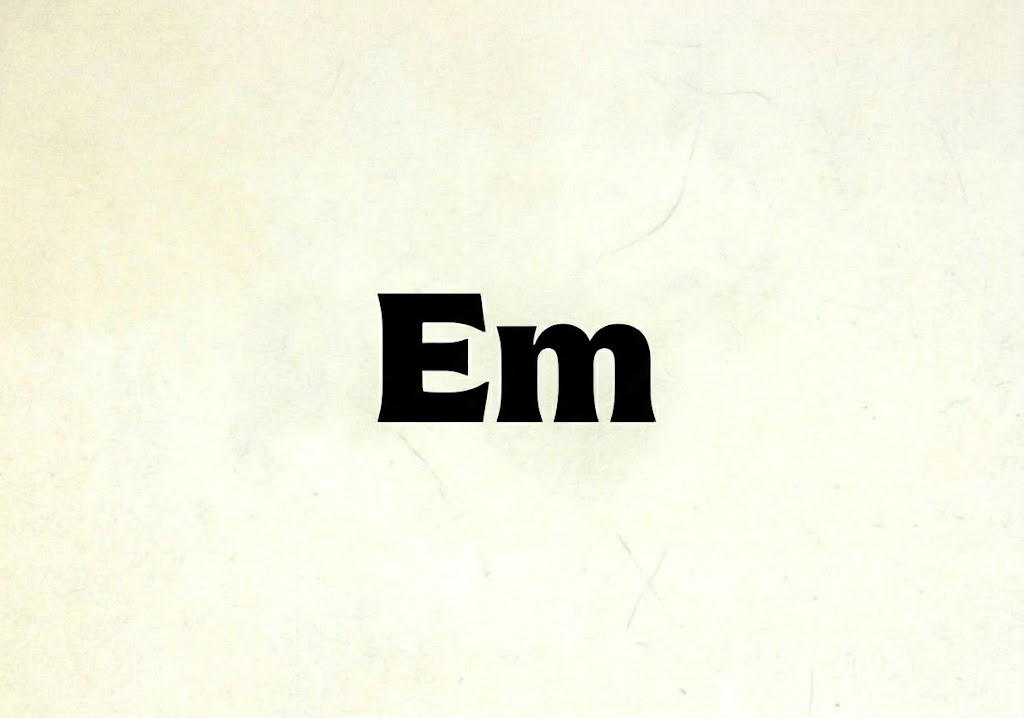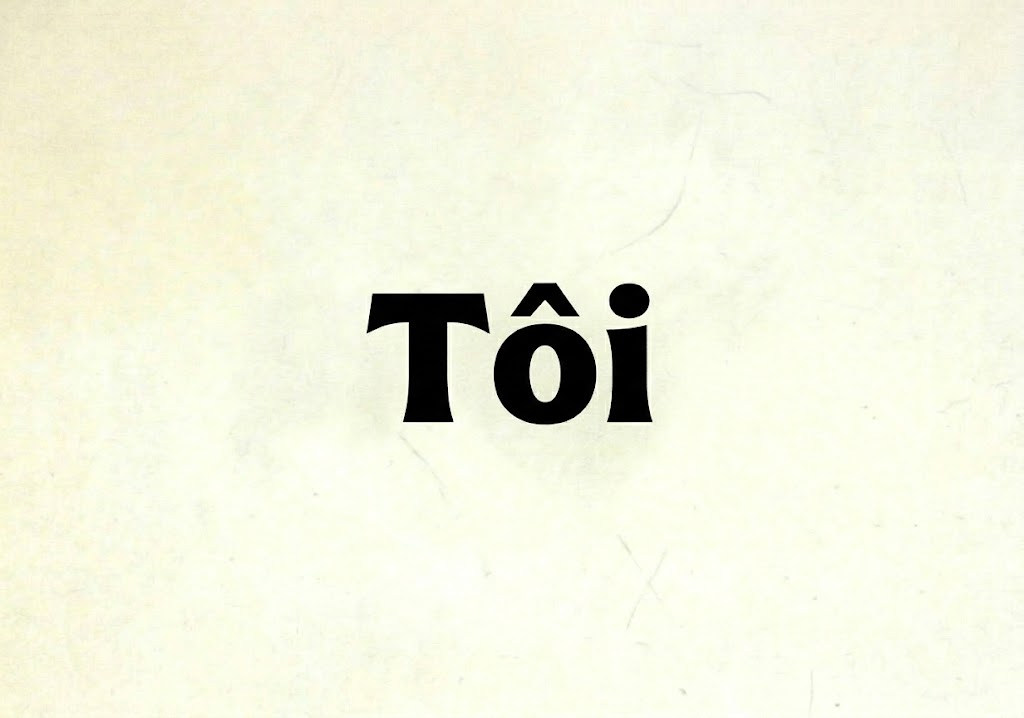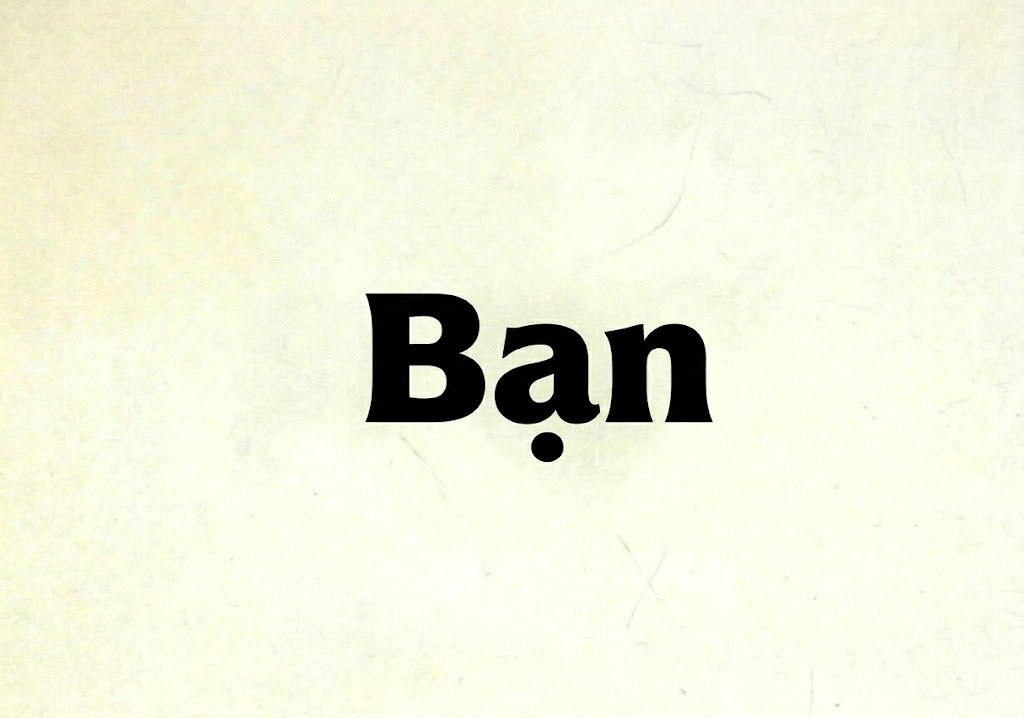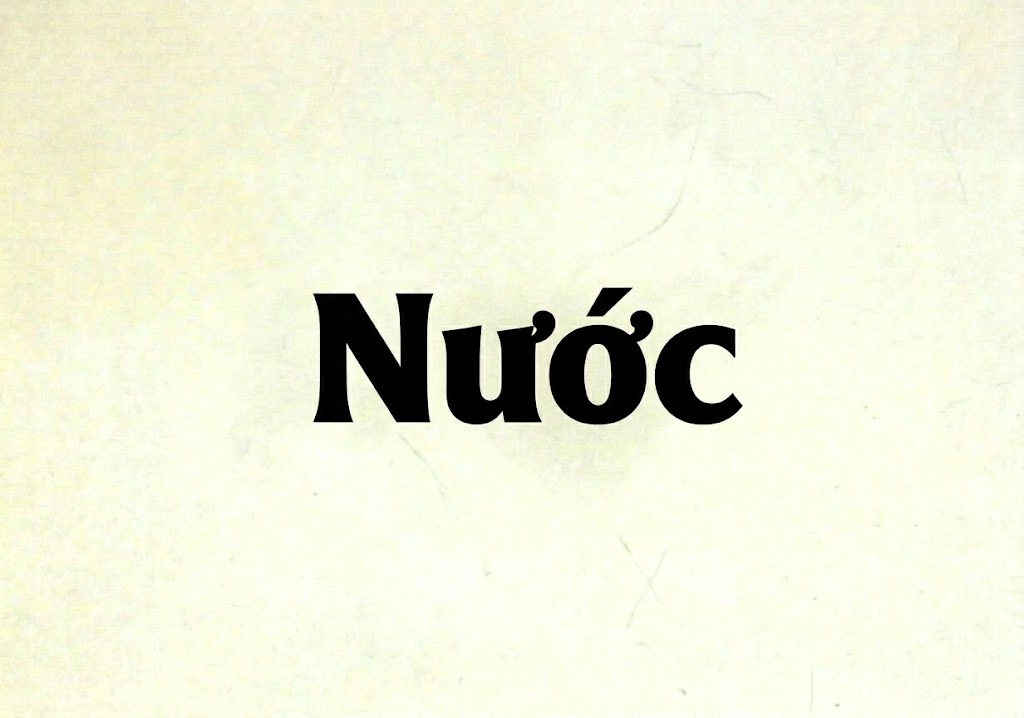
1FTV Akina
Trong thế giới thiết kế đồ họa và sáng tạo nội dung hiện đại, việc sở hữu một phông chữ tiêu đề vừa có độ dày ấn tượng lại vừa mang tính nghệ thuật độc đáo luôn là lợi thế lớn.
Đa số các phông chữ siêu đậm thường đi theo thiên hướng thô cứng, hình khối, dễ gây cảm giác nhàm chán cho người xem.
Nếu bạn đang tìm kiếm một sự kết hợp hoàn hảo giữa nét chữ dày dặn, vững chãi với các đường uốn lượn đầy cá tính, thì font 1FTV Akina chính là câu trả lời dành cho bạn.
Giới thiệu về font 1FTV Akina
Font 1FTV Akina là một phông chữ hiển thị mang đậm phong cách đồ họa hiện đại, pha trộn chút hơi thở văn hóa đại chúng châu Á đầy sinh động.
Nhờ đó, phông chữ có khả năng hiển thị sắc nét, giúp các nhà thiết kế tự tin sử dụng trên nhiều phần mềm đồ họa hiện nay mà không sợ bị vỡ nét.
Đặc điểm nổi bật của phong cách thiết kế Akina
Sức hút khác biệt của font 1FTV Akina đến từ kết cấu nét siêu dày kết hợp cùng những đường vát góc và cách điệu vô cùng tinh tế.
Các ký tự như k, x, f, w được tạo điểm nhấn bằng những đường cong điệu nghệ, mang lại cảm giác vừa mềm mại, vừa tràn đầy năng lượng.
Bộ font này hỗ trợ trọn vẹn cả hệ thống chữ thường bên cạnh bộ chữ viết hoa, tạo điều kiện thuận lợi cho việc phân tách các tầng nội dung.
Khoảng trống bên trong của các con chữ được tính toán khoa học, giúp văn bản luôn rõ ràng và không bị dính đặc khi thu nhỏ bố cục.
Để phông chữ vận hành mượt mà trên mọi hệ thống máy tính, phiên bản font 1FTV Akina đã trải qua quy trình căn chỉnh thông số kỹ thuật vô cùng nghiêm ngặt.
Hệ thống khoảng cách chữ và độ giãn dòng đã được căn chỉnh chuẩn xác, giúp các từ khi đứng cạnh nhau luôn giữ được sự liền mạch, hài hòa.
Bên cạnh hệ thống chữ cái hoa và thường đồng bộ, phông chữ còn tích hợp đầy đủ dãy số từ 0-9 cùng các ký tự đặc biệt, dấu câu thông dụng (.,:;'"(!?)+-*/=).
Tiện ích này giúp bạn thoải mái biến hóa nội dung quảng cáo hoặc biên tập video mà không lo bị lỗi hiển thị hay thiếu ký tự khi gõ.
Hình ảnh demo thực tế của font 1FTV Akina
Để giúp bạn dễ dàng hình dung khả năng co giãn và hiển thị linh hoạt của phông chữ này trên các kích thước khác nhau, hãy cùng xem qua bảng mô phỏng thực tế:
Kích thước nhỏ (12pt – 24pt): Các nét chữ đậm và bộ chữ thường vẫn hiển thị rất rõ ràng, ngay ngắn, dễ đọc trên màn hình điện thoại di động.
Kích thước lớn (36pt – 72pt): Đây là không gian lý tưởng để font chữ phô diễn toàn bộ sức mạnh nghệ thuật của mình, tạo hiệu ứng thị giác mạnh mẽ cho các tiêu đề chính.
Ứng dụng của font Akina trong thiết kế đồ họa và làm video
Nhờ sở hữu nét cá tính bứt phá và cấu trúc hoa – thường linh hoạt, font 1FTV Akina mở ra không gian ứng dụng rộng lớn cho các dự án marketing và truyền thông:
Thiết kế thumbnail Youtube và ảnh thu nhỏ mạng xã hội: Đây là vũ khí hạng nặng để tăng tỷ lệ nhấp chuột. Khi kết hợp các khối chữ viết chữ thường xen lẫn chữ hoa với tông màu nổi bật trên nền tối, dòng tiêu đề sẽ lập tức đập vào mắt người xem.
Làm tiêu đề video ngắn (Tiktok, Shorts, Reels): Rất thích hợp để làm các cụm từ từ khóa chính, tiêu đề mở đầu video phong cách trẻ trung, giúp giữ chân người xem lướt chậm lại để theo dõi.
Banner và poster quảng cáo ngành giải trí, thời trang: Hoàn hảo cho các poster sự kiện nghệ thuật, banner ngành hàng ăn uống, thời trang streetwear cá tính hoặc các sản phẩm sáng tạo hướng tới giới trẻ.
Nhận diện thương hiệu và bao bì sản phẩm: Phù hợp làm logo dạng chữ khối, artwork hoặc thiết kế nhãn mác cho các thương hiệu trà sữa, bánh ngọt, studio sáng tạo cần sự phá cách, mộc mạc và độc đáo.